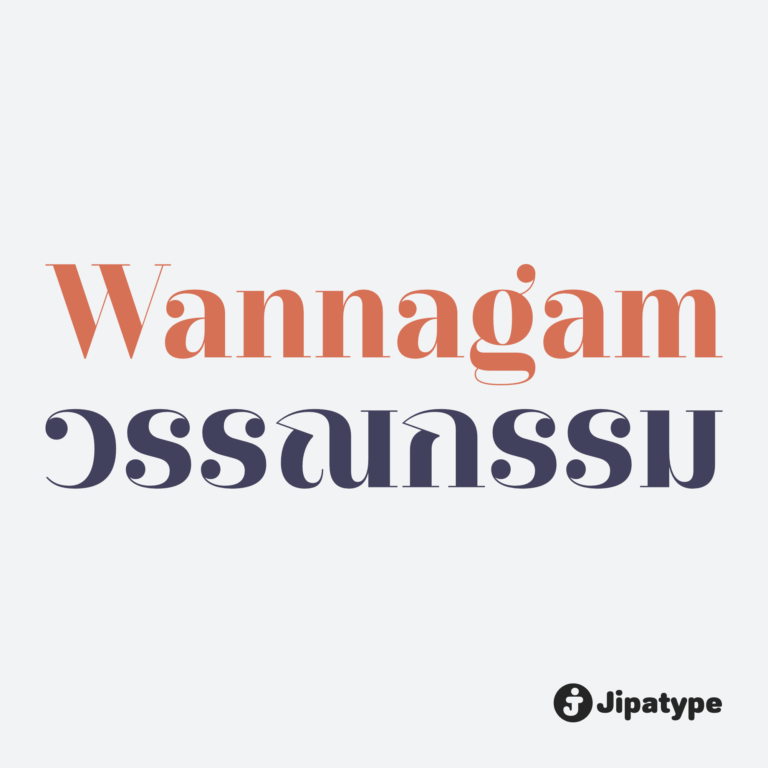
อลเวง | Onlaweng
Onlaweng เป็นแบบอักษรพาดหัว (Display Font) ที่สลับตำแหน่งน้ำหนักของเส้นแนวนอนและแนวตั้ง (Reverse Contrast) และมีโครงสร้างที่ดูแล้วไม่แข็งแรง ให้อารมณ์เหมือนเขียนด้วยปากกามาร์กเกอร์หัวตัด เมื่อรวมองค์ประกอบเหล่านี้เข้าด้วยกัน ทำให้แบบอักษรนี้ดูแปลกประหลาด และดูสับสน แต่ยังอ่านได้
นิคม | Nikhom
Nikhom เป็นชุดแบบอักษร Sans Serif ที่เน้นความเรียบง่ายและดูสะอาดตา มีจุดเด่นอยู่ที่การออกแบบรูปทรงตัวอักษรให้มีความแบนราบทั้งส่วนยอดและส่วนฐาน เพื่อให้เส้นสายดูขนานไปกับเส้นฐาน (Baseline) และเส้น x-height โครงสร้างนี้ช่วยให้ภาพรวมของข้อความดูเป็นระเบียบ มั่นคง และสบายตา
บรรณาธิการลูปเลส | Bunnathikarn Loopless
Bunnathikarn Loopless เป็นการต่อยอดดีไซน์จากตระกูล Bunnathikarn โดยปรับเปลี่ยนโครงสร้างอักษรไทยให้เป็นแบบไม่มีหัว เพื่อมอบภาพลักษณ์ที่ดูทันสมัย โฉบเฉี่ยว และมีความเป็นสากลมากยิ่งขึ้น เหมาะอย่างยิ่งสำหรับงานแบรนด์ดิ้งแฟชั่น สินค้าลักชัวรี่ สื่อไลฟ์สไตล์ หรือหัวข้อความ ที่ต้องการสะท้อนรสนิยมที่เหนือระดับและบุคลิกที่มั่นใจ
บรรณาธิการ | Bunnathikarn
Bunnathikarn เป็นแบบอักษรแซนเซอริฟ โดยมีชุดแบบอักษรไทยเป็นประเภทมีหัว ที่ผสมผสานความคลาสสิกเข้ากับความร่วมสมัยได้อย่างลงตัว โดดเด่นด้วยเส้นสายแบบ High Contrast ที่มีการตัดกันระหว่างเส้นหนาและเส้นบางอย่างชัดเจน ให้คาแรคเตอร์ที่ดูหรูหรา สง่างาม และมีความเฉียบคม แฝงไปด้วยความน่าเชื่อถือแบบมืออาชีพ
อัตถะลูปเลส | Attha Loopless
Attha Loopless เป็นชุดตัวอักษร Sans-serif สไตล์โมเดิร์นที่ถูกพัฒนาต่อยอดขึ้นจาก อัตถะ | Attha โดยปรับเปลี่ยนให้เป็นอักษรไทยแบบ “ไม่มีหัว” ทำให้มีรูปลักษณ์ที่โดดเด่นและเป็นสากลยิ่งขึ้น
อัตถะ | Attha
Attha คือชุดตัวอักษรประเภท Sans-serif สไตล์โมเดิร์นที่เน้นโครงสร้างแบบ เรขาคณิต ที่มีความสมมาตรและความชัดเจนในการสื่อสาร โดดเด่นด้วยการออกแบบอักษรไทยแบบ “มีหัว” ซึ่งถูกปรับปรุงให้ดูร่วมสมัยและเป็นระเบียบ หัวของตัวอักษรไทยมีขนาดที่พอเหมาะและได้รับการออกแบบอย่างพิถีพิถันเพื่อรักษามาตรฐานการอ่าน
บ๊วยหวาน | Buaywan
Buaywan เป็นชุดตัวอักษรที่โดดเด่นด้วยลายเส้นที่มีน้ำหนักตัดกันอย่างชัดเจน ให้ความรู้สึกเหมือนการตวัดปลายพู่กันหรือปากกาหัวตัด เส้นสายมีความโค้งมน พลิ้วไหว และดูเป็นธรรมชาติ ซึ่งช่วยลดทอนความแข็งกระด้าง ทำให้ตัวอักษรดูมีความ “หวาน” นุ่มนวล และเป็นมิตร ตามชื่อของฟอนต์
ปฐมวัย | Pathomwai
Pathomwai เป็นชุดแบบอักษรที่โดดเด่นด้วยรูปลักษณ์ที่ให้ความรู้สึกนุ่มนวล อบอุ่น และเป็นมิตรอย่างยิ่ง ตัวอักษรถูกออกแบบให้มีลักษณะปลายมน ทั้งในส่วนของตัวอักษรไทยแบบมีหัวและตัวอักษรละติน ลดทอนความแข็งกระด้างของเส้นสาย ทำให้ดูเหมือนลายมือที่เขียนด้วยปากกาหัวมนอย่างบรรจง
รมควัน | Romkhwan
รมควัน เป็นฟอนต์แนวสลับเซอริฟ ที่มีความสนุกแบบไม่หลุดกรอบ เล่นได้แต่ไม่หลุดโลก มีคาแรกเตอร์ที่ดูขี้เล่นแต่ยังคงสมดุล เหมาะกับงานที่อยากให้ดูสบาย ๆ แต่ยังมีโครงสร้าง
ประจักษ์ | Prachak
Prachak เป็นแบบอักษรที่ได้รับแรงบันดาลใจจากแบบอักษรตระกูลโป้งโดยเฉพาะแบบอักษรโป้งไม้ แบบอักษรโป้งนั้นเป็นที่นิยมในช่วงหลังการเปลี่ยนแปลงการปกครอง 2475 เป็นช่วงที่วงการหนังสือพิมพ์เติมโตอย่างรวดเร็ว ตัวโป้งถูกใช้บนพาดหัวหนังสือพิมพ์เพื่อสร้างความสะดุดตา โดดเด่น
วรรณกรรม | Wannagam
Wannagam เป็นแบบอักษรเซอริฟที่ได้รับแรงบันดาลใจจากฟอนต์สุดคลาสิก Didot ตัวอักษรมีโครงสร้างที่ประณีตและสัดส่วนที่สมดุล เส้นสายของตัวอักษรให้ความรู้สึกสง่างาม แข็งแรง และน่าเชื่อถือ ในขณะเดียวกันยังคงไว้ซึ่งความอ่อนช้อยและความกลมกลืน เหมาะสื่อประชาสัมพันธ์ที่ต้องการความละเอียดอ่อน เช่น นิตยสาร ปกหนังสือ งานพิมพ์หรูหรา
หวานละไม | Wanlamai
Wanlamai เป็นแบบอักษรที่โดดเด่นด้วยเส้นสายโค้งมน นุ่มนวล โครงสร้างตัวอักษรได้รับการออกแบบให้กลมกลืนทั้งภาษาไทยและละติน สร้างความรู้สึกอบอุ่นและเข้าถึงง่าย ความเรียบง่ายที่ดูทันสมัยทำให้ Wanlamai เหมาะสำหรับงานที่ต้องการเน้นความชัดเจน เช่น สื่อออนไลน์ บรรจุภัณฑ์ หรือโปสเตอร์โฆษณา
นิมิต | Nimit
นิมิต เป็นแบบอักษรที่เลียนแบบสไตล์การเขียนด้วยปากกาหัวตัด เพื่อให้ลักษณะตัวอักษรออกมาเป็นอักษรวิจิตร เหมาะสำหรับสื่อประชาสัมพันธ์ที่การสื่อถึงความเก่าแก่ มีมนต์ขลัง
ขายส่ง | Khaisong
ขายส่ง เป็นแบบอักษรคอนทราสต์แซนเซอริฟ ตัวอักษรมีลักษณะ Geometric ให้ความรู้สึกเป็นทางการแต่ไม่แข็งกระด้าง มีความเรียบง่าย เหมาะสำหรับสื่อประชาสัมพันธ์ที่ต้องการสื่อสารเนื้อหาเชิงธุรกิจและองค์กร โดยยังคงความอ่านง่ายและความเป็นมืออาชีพ
อภิรมย์ | Aphirom
อภิรมย์ เป็นแบบอักษรคอนทราสต์แซนเซอริฟ มีโครงสร้างตัวอักษรที่แคบ มีเส้นแนวตั้งและแนวนอนเปรียบต่างกัน ให้ความรู้สึกผอมเพรียวและสวยงามเห็นแล้วรู้สึกได้ถึงความอภิรมย์ เหมาะสำหรับสื่อประชาสัมพันธ์ที่ต้องการสื่อสารเรื่องความงาม ความสุขสงบ ธรรมชาติ